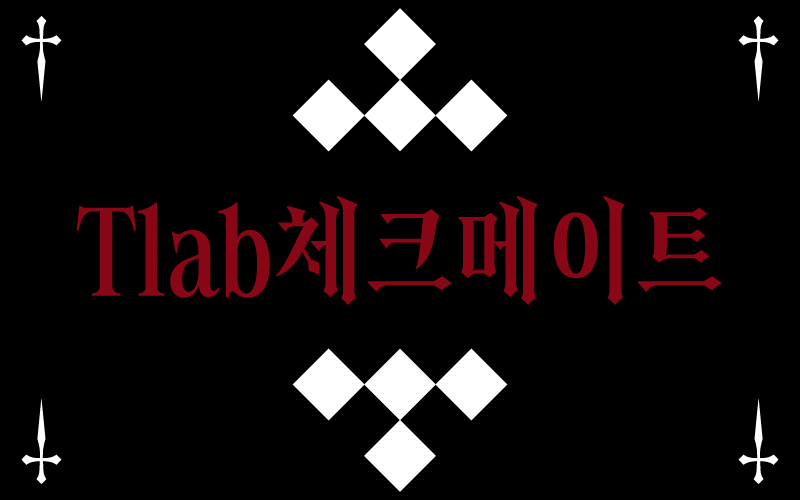
TlabCheckmate
1 Style - Regular《Tlab체크메이트》는 명조 계열의 장체 디스플레이 서체로, 강한 획 대비와 안정적인 구조 위에 뾰족한 획과 날카로운 세리프를 더해 강렬하면서도 신비로운 인상을 만들어냅니다. Latin-1 Supplement를 지원하여 다양한 서유럽권 언어를 표현할 수 있으며, 유니코드 체스 기호 역시 포함되어 있습니다. 체스에서 상대의 왕을 완전히 포위해 승리를 확정짓는 순간에서 이름을 가져온 것처럼, 《Tlab체크메이트》와 《Tlab체크메이트 Deco》는 긴장감과 강렬한 승리의 이미지를 담아냅니다.